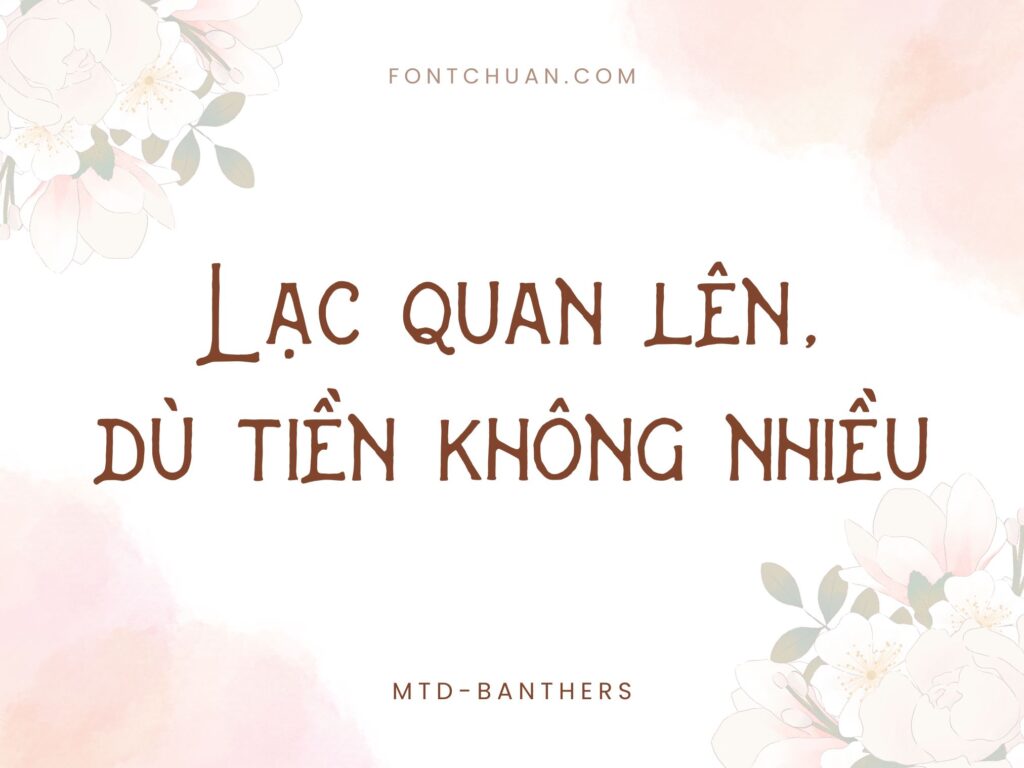
Font MTD Banthers Việt Hóa
Banthers là một font chữ ấn tượng được thiết kế bởi Swistblnk Std, mang phong cách viết tay đầy cá tính và mạnh mẽ. Với thiết kế đầy sự sáng tạo, Banthers giúp tạo nên những sản phẩm đồ họa độc đáo, phù hợp với nhiều phong cách thiết kế khác nhau. Để giúp font này trở nên dễ sử dụng hơn cho cộng đồng thiết kế Việt Nam, Mộc Hạ đã Việt hóa Banthers, giúp nó hỗ trợ đầy đủ tiếng Việt cùng hơn 200 ngôn ngữ khác trên thế giới. Font Banthers Việt hóa đã được thành viên Font Chuẩn sưu tầm và đăng tải, mang đến lựa chọn phong phú hơn cho các dự án sáng tạo.
Về đặc điểm thiết kế, Banthers mang đậm phong cách viết tay cổ điển nhưng vẫn giữ được nét hiện đại. Các ký tự có sự liên kết linh hoạt, giúp tạo cảm giác tự nhiên khi sử dụng. Font này rất thích hợp cho các thiết kế logo, thương hiệu cá nhân, typography nghệ thuật và tiêu đề lớn. Ngoài ra, Banthers còn phù hợp cho các lĩnh vực như quảng cáo, thiệp cưới và các dự án sáng tạo đòi hỏi sự phá cách. Đặc biệt, font này là lựa chọn lý tưởng cho các sự kiện như Valentine, Sinh nhật và các dịp lễ hội.